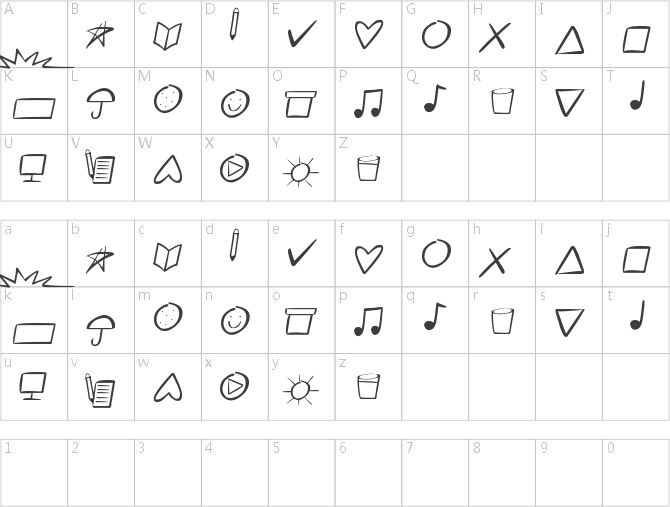
字體名稱(chēng): My Shap
My Shapes
My Shapes字體字庫(kù)是一款讓人賞心悅目、百看不厭的英文字體,適合各類(lèi)廣告和產(chǎn)品包裝設(shè)計(jì)應(yīng)用,字體大小0.01MB,格式為ttf字體,上傳用戶(hù)是@小咖,作者/版權(quán)方為未知